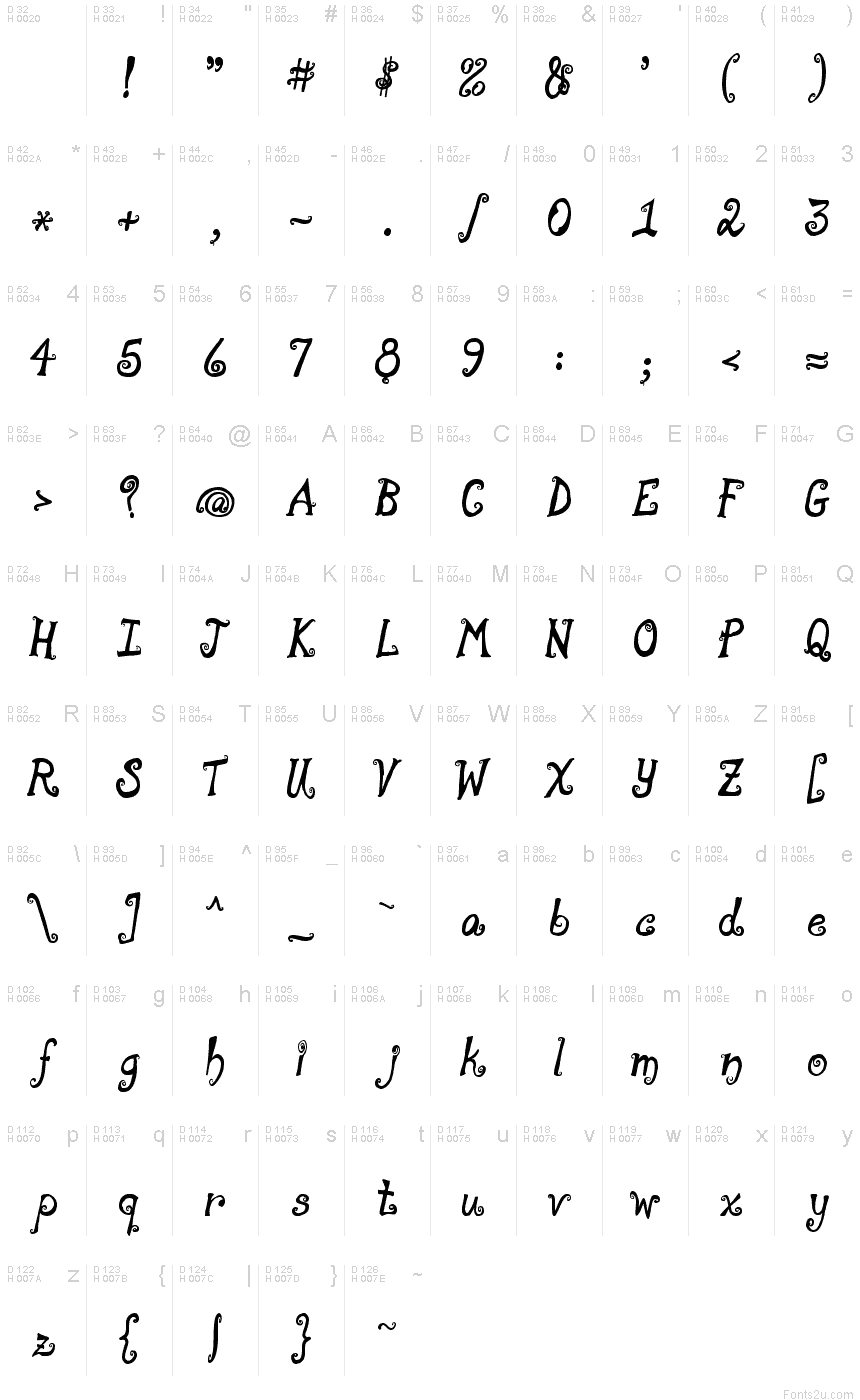
moonpie a la monde
Moonpie a la Monde autorstwa Stevena J. Lundeena to darmowy, ozdobny krój pisma typu script z pętelkami i spiralnymi wycięciami, które zamieniają każde słowo w ciąg dekoracyjnych zawijasów. Litery powtarzają ten sam zaokrąglony, odręczny ruch, dzięki czemu czcionka przypomina bardziej ozdobny napis niż typowy font do składu tekstu.
Moonpie a la Monde świetnie sprawdzi się na opakowaniach słodyczy, tytułach plakatów, logotypach butików, kartkach z zaproszeniami i szyldach kawiarni, wszędzie tam, gdzie odrobina fantazji pomaga przekazać komunikat. Pasuje również do krótkich cytatów, okładek albumów, etykiet rękodzielniczych i nagłówków sezonowych, które potrzebują dekoracyjnej dynamiki, zachowując przy tym przyjazny, odręczny charakter.